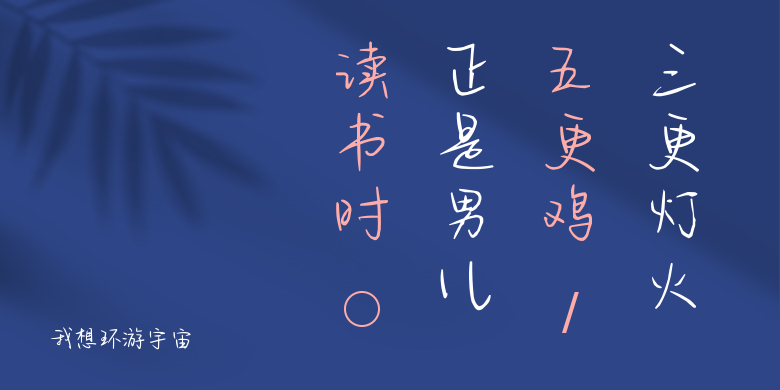
我想环游宇宙
我想环游宇宙,这款字体结构工整、笔画清晰,兼顾美观与易读性,适用于标题、正文、海报、包装、LOGO 等多种场景。字形优雅稳定,风格百搭耐看,适配日常排版与创意设计,让文字呈现更舒适、更具质感。我想环游宇宙一笔一画,皆是细节,以均衡的比例、流畅的线条打造舒适视觉体验,字形端正大气,风格简约现代。无论是商业设计、品牌宣传还是日常排版,都能轻松驾驭,让文字更有格调与力量。我想环游宇宙字体下载。